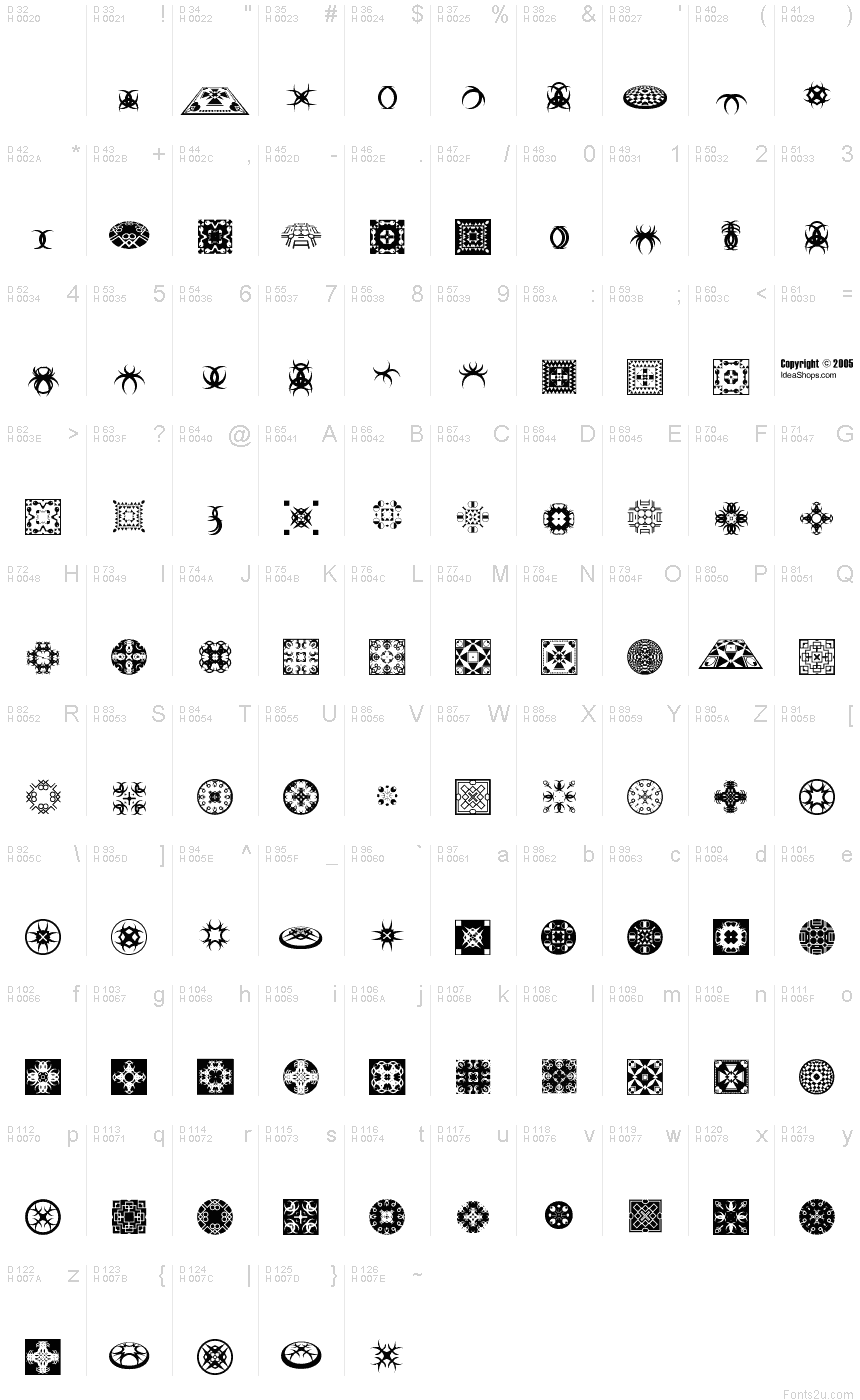
FontCo Designs 2 di FontCo è un font dingbat esoterico gratuito, costruito attorno a medaglioni audaci, petali specchiati e motivi geometrici ripetuti. L'estetica oscilla tra l'occulto e l'ornamentale, con esplosioni di stelle, sigilli circolari, anelli ed emblemi quadrati che richiamano diagrammi sacri e vecchi manuali di loghi.
È ideale ovunque un design necessiti di un tocco simbolico piuttosto che di semplici lettere: su copertine di album, bordi di poster, branding ispirato ai tarocchi, copertine di zine, sigilli per inviti o titoli. Essendo un font gratuito, è particolarmente utile per inserire ornamenti, monogrammi e marcatori decorativi, poiché le forme sono già bilanciate e complete.